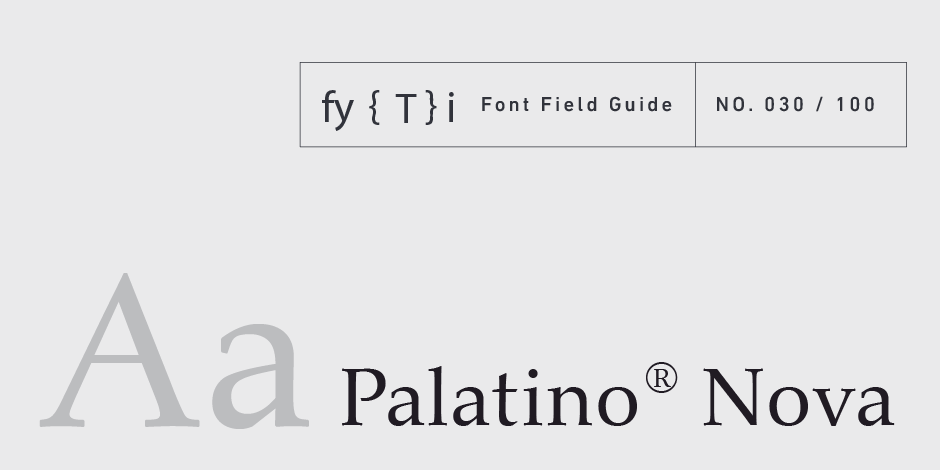
Palatino® Nova Police Guide de terrain
FOUNDRY : Linotype
CONCEPTEUR : Hermann Zapf & Akira Kobayashi
CLASSIFICATION : Ancien style à empattement
Meilleures pratiques
En raison de ses proportions élargies, le Palatino Nova peut, et dans de nombreux cas doit, avoir des longueurs de ligne un peu plus importantes. C'est également un caractère qui ne fatigue pas l'œil lorsque des longueurs de lignes plus importantes sont spécifiées.
Famille
La famille Palatino Nova se compose de quatre graisses de caractères romains, chacune avec son équivalent italique, et de deux titrages polices - Palatino Nova Pro Titling et Palatino Nova Pro Imperial.
Police Les faits
- Le dessin a été nommé d'après Giambattista Palatino, un maître calligraphe de l'époque de Léonard de Vinci.
- Palatino était la police de caractères préférée de Zapf.
- Contrairement à la croyance populaire, Palatino n'est pas la première police de caractères d'Hermann Zapf. Il s'agit toutefois de sa première police de caractères à succès commercial.
Racines
Le Palatino original a été taillé dans le métal par August Rosenberger à la fonderie de D. Stempel AG à Francfort, et publié en 1950. Le Palatino a ensuite été adapté à la composition mécanique sur la machine Linotype et est devenu l'un des caractères les plus utilisés du XXe siècle.
Hermann Zapf et Akira Kobayashi ont redéfini le Palatino pour le XXIe siècle, créant le Palatino Nova. Commercialisée par Linotype en 2005, la famille Palatino Nova fait partie de la Platinum Collection de Linotype.
Lisibilité
Les proportions plutôt larges du Palatino Nova et l'ouverture de ses guichets lui permettent de rester lisible dans toutes les tailles de caractères, à l'exception des plus petites. Les formes de caractères distinctives, qui donnent au caractère sa personnalité, assurent également une grande lisibilité typographique.
Comment repérer Palatino Nova
Autres choix
L'association parfaite